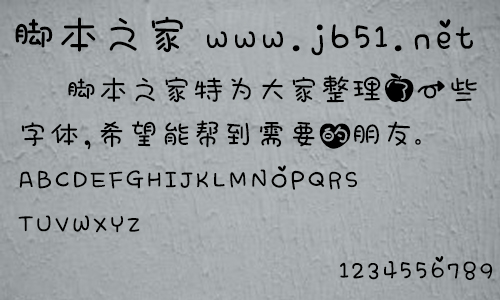
小蘋果字體是一款中文卡通字體,這款字體筆觸較為粗實(shí),字體清晰明朗,字形圓潤(rùn)可愛(ài),該字中點(diǎn)綴著蘋果的元素,看上去煞是可愛(ài),適合應(yīng)用于藝術(shù)設(shè)計(jì)、平面宣傳設(shè)計(jì)、網(wǎng)頁(yè)設(shè)計(jì)、書法字帖、海報(bào)設(shè)計(jì),兒童讀物等,需要的朋友可以前來(lái)本站下載。